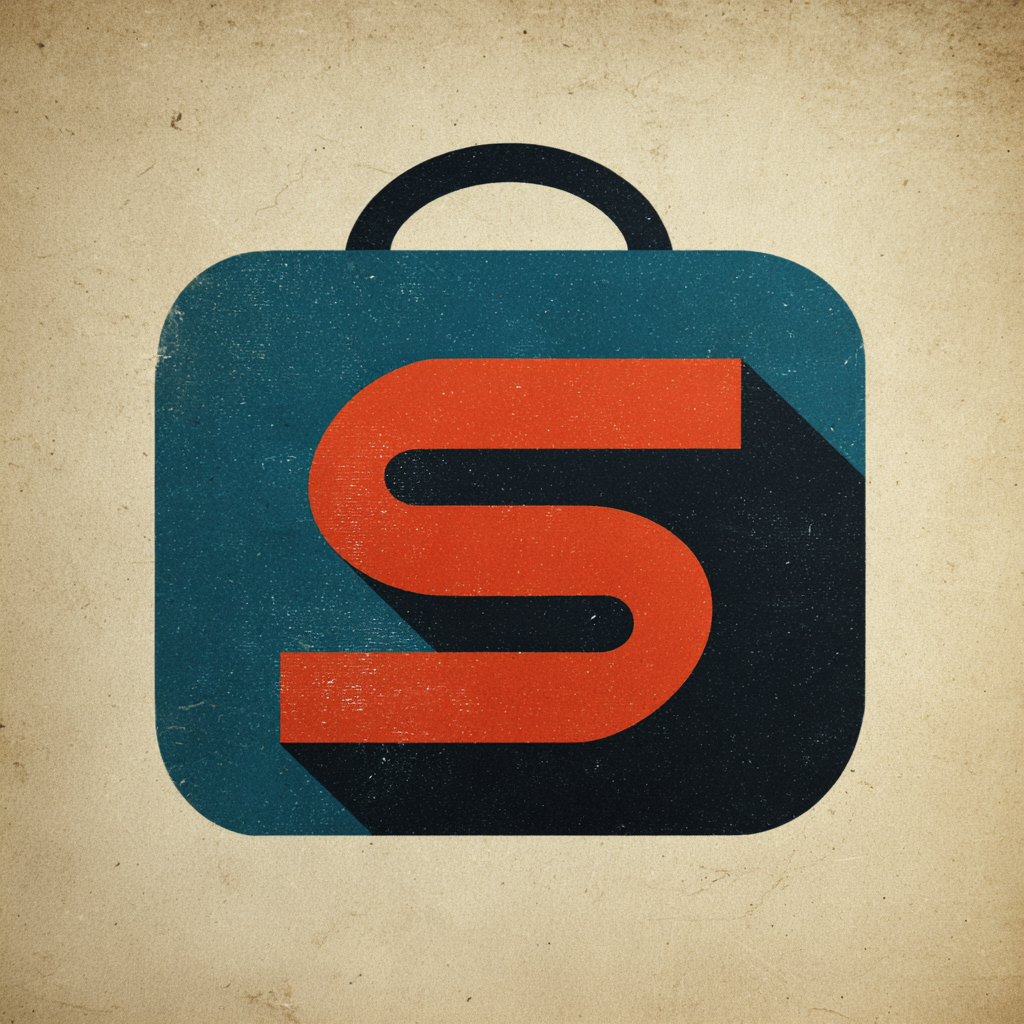
스마트스토어를 처음 시작하거나 리브랜딩을 고민하고 있다면, 가장 먼저 눈에 들어오는 요소 중 하나가 바로 ‘로고’예요. 로고는 브랜드의 첫인상이자, 소비자가 기억하는 가장 강력한 시각적 아이덴티티랍니다. 🛍
특히 요즘처럼 온라인 경쟁이 치열한 시대에는, 스마트스토어의 신뢰감과 차별성을 로고 하나로 보여줘야 할 때가 많아요. 그래서 오늘은 전문가들이 추천하는 스마트스토어 로고 스타일과 디자인 팁을 본격적으로 소개할게요!
🎨 로고 디자인의 중요성과 기원
로고는 단순한 그림이 아니에요. 브랜드의 얼굴이자, 고객과의 첫 만남에서 인상을 좌우하는 핵심 요소예요. 상호명보다도 먼저 시선을 끄는 게 바로 이 ‘로고’인 만큼, 제대로 만들어야 해요.
로고의 역사는 고대 이집트의 상형문자에서 시작됐다고 해요. 상인들이 자신들의 물건에 새긴 상징적인 기호가 현대 로고의 시작이었죠. 이후 중세 유럽에서는 상인의 가문이나 길드를 상징하는 문장(紋章)으로 발전했고, 산업화 시기엔 기업의 공식 마크로 자리 잡았답니다.
스마트스토어처럼 디지털 기반의 비즈니스에서는 로고가 더 중요한 이유가 있어요. 오프라인 매장과 달리 손님이 직접 만지는 물건이나 분위기를 느낄 수 없기 때문에, 화면에서 보여지는 로고와 썸네일이 곧 매장의 '느낌'이 되기 때문이에요.
그만큼 전문성과 신뢰감을 주는 디자인, 그리고 브랜드 정체성이 잘 녹아든 로고는 고객의 기억 속에 깊게 남게 되죠. 스마트스토어 운영자라면 반드시 로고에 신경 써야 해요.
📌 로고 유형별 특성 비교표
로고 유형 특징 예시 브랜드 활용성 텍스트 로고 상호나 브랜드명을 글자 형태로 표현 Google, Samsung 높음 심벌 로고 기호나 그림으로 브랜드 상징화 Apple, Nike 중간 조합형 로고 텍스트 + 아이콘 병행 스타벅스, 배달의민족 매우 높음 앰블럼 로고 문장 형태로 구성된 로고 하버드 대학교, 포르쉐 낮음 내가 생각했을 때 스마트스토어 로고는 '조합형'이 가장 무난하면서도 브랜드성을 잘 살릴 수 있는 스타일 같아요. 단순히 글자만 있는 로고보다, 아이콘이나 이미지가 같이 들어가면 훨씬 기억에 남거든요!
다음은 2025년에 가장 인기 있을 것으로 예상되는 스마트스토어 로고 스타일 트렌드를 살펴볼게요! ✨
🌟 2025년 스마트스토어 로고 트렌드
2025년의 스마트스토어 로고 트렌드는 ‘간결함’과 ‘브랜드 스토리 전달력’이 핵심이에요. 복잡하고 화려한 로고보다는, 직관적이고 명확한 메시지를 주는 디자인이 인기를 끌고 있죠.
요즘 소비자들은 브랜드와의 감성적 연결을 중요하게 생각해요. 그래서 로고 하나에도 감성, 브랜드 철학, 정체성이 담겨 있어야 해요. 한눈에 브랜드 분위기를 알 수 있어야 한다는 뜻이죠.
특히 모바일 환경이 지배적인 지금, 작은 스마트폰 화면에서도 선명하게 보이고 기억에 남을 수 있는 디자인이 필요해요. 아이콘과 텍스트가 조화롭게 구성되어야 하며, ‘응답형 로고(Responsive Logo)’ 형태도 각광받고 있어요.
응답형 로고는 PC, 태블릿, 모바일 등 다양한 환경에 따라 형태나 배치가 달라지는 유연한 디자인을 말해요. 이 방식을 적용하면 어떤 기기에서도 브랜드 일관성을 유지할 수 있답니다.
📊 2025 로고 트렌드 핵심요소
트렌드 요소 설명 추천 적용 대상 미니멀리즘 불필요한 장식 없이 핵심만 표현 생활용품, 의류 플랫 디자인 입체감 없이 깔끔한 2D 형태 디지털 제품, IT 컬러 포인트 한두 가지 색으로 강한 인상 화장품, 식품 모노라인 균일한 두께의 선으로 구성 핸드메이드, 감성몰 응답형 로고 기기별로 최적화되는 변형 로고 모든 스마트스토어 이런 트렌드를 참고해서, 나의 스마트스토어 로고에도 트렌디한 감성을 더해보는 건 어떨까요? 너무 유행만 좇기보다는 브랜드의 개성을 반영하는 게 더 중요하다는 것도 잊지 마세요! 🧠
다음 섹션에서는 실제 전문가들이 추천하는 7가지 스타일을 소개할게요. 스마트스토어 콘셉트에 맞는 로고 스타일을 찾는 데 도움이 될 거예요! 💡
💡 전문가 추천 스타일 7가지
전문 디자이너들이 스마트스토어 로고를 만들 때 자주 추천하는 스타일은 다양하지만, 이 중 7가지가 특히 많이 쓰이고 있어요. 각각의 스타일은 브랜드의 성격, 타깃 고객, 판매 제품과도 연결되기 때문에, 자신의 스토어와 어울리는 스타일을 고르는 게 중요해요.
첫 번째로는 '핸드레터링 스타일'이에요. 이 스타일은 마치 직접 쓴 듯한 감성을 전할 수 있어서 수제 제품, 소규모 공방 브랜드에 잘 어울려요. 개성과 따뜻한 분위기를 동시에 줄 수 있죠.
두 번째는 '미니멀 라인 스타일'인데요, 단순한 선과 형상으로 구성된 이 스타일은 시선을 집중시키고 고급스러운 느낌을 주는 데 탁월해요. IT 제품이나 라이프스타일 브랜드에 적합하죠.
세 번째는 '빈티지 뱃지 스타일'이에요. 예전 마크나 스탬프처럼 디자인된 이 스타일은 클래식하면서도 신뢰감을 주기 때문에 커피, 가구, 캠핑용품 같은 분야에 잘 어울려요.
📋 추천 스타일 7종 비교표
스타일명 주요 특징 추천 업종 핸드레터링 직접 쓴 듯한 감성 공방, 수공예, 디저트 미니멀 라인 단순함, 고급스러움 라이프스타일, 테크 빈티지 뱃지 고전적인 느낌, 신뢰감 커피, 캠핑, 남성브랜드 일러스트형 캐릭터나 도형 중심 아동, 반려동물 심볼 중심 기억에 남는 상징 사용 모든 분야 워드마크형 글자 중심, 이름 강조 브랜드 인지도 필요 분야 모노그램 이니셜 활용 패션, 전문성 강조 브랜드 각 스타일마다 매력이 다르기 때문에, 단순히 유행만 따르기보다는 브랜드 성격과 고객층을 고려해서 선택하는 게 좋아요. 예를 들어, 아동용 제품을 판매하는 스토어라면 일러스트 스타일이 어울리고, 클래식한 맛집이라면 빈티지 뱃지가 딱이에요.
이제 스타일을 골랐다면, 어떤 색과 글자체를 조합해야 더 돋보일까요? 다음 섹션에서 컬러와 타이포그래피에 대해 알려드릴게요! 🎯
🎨 컬러와 타이포그래피의 조화
로고에서 색상과 글꼴은 단순한 시각 요소가 아니라, 브랜드의 분위기와 정체성을 전달하는 언어예요. 어떤 색을 쓰느냐, 어떤 폰트를 고르느냐에 따라 고객이 느끼는 브랜드 이미지는 전혀 달라진답니다.
예를 들어, 파란색은 신뢰감과 안정감을 주고, 빨간색은 열정과 에너지를 상징해요. 녹색은 친환경과 건강을, 검정은 고급스러움과 세련됨을 표현하죠. 스마트스토어가 어떤 제품을 파느냐에 따라 전략적으로 색상을 선택해야 해요.
또한 폰트는 브랜드의 성격을 정하는 핵심 요소 중 하나예요. 굵고 둥근 폰트는 친근하고 캐주얼한 느낌을 주고, 세리프(Serif) 폰트는 클래식하고 고급스러운 분위기를 자아내요. 반면 산세리프(Sans-serif)는 현대적이고 깔끔한 인상을 주죠.
특히 모바일에서 로고가 작게 표시되는 스마트스토어 환경에선 ‘가독성’이 중요해요. 너무 복잡하거나 장식이 많은 폰트는 피하고, 간결하면서도 개성 있는 폰트를 고르는 게 좋아요.
🎯 색상 & 타이포 조합 예시
컬러 느낌 추천 업종 어울리는 폰트 🔵 파랑 신뢰, 안정감 전자제품, 교육 Noto Sans, Pretendard 🔴 빨강 활력, 자극 패션, 뷰티, 식품 BM Jua, Gmarket Sans 🟢 초록 자연, 건강 헬스, 친환경 Cafe24 Ssurround, Nanum Gothic ⚫ 검정 세련됨, 고급 럭셔리, 서비스 Roboto, Spoqa Han Sans 🟡 노랑 유쾌함, 창의 문구, 키즈, 팬시 UhBee Seulvely, Tmon몬소리 컬러를 정할 때는 브랜드의 톤앤매너(Tone & Manner)를 고려해야 해요. 명확한 브랜딩 컬러가 있어야 일관된 인상을 줄 수 있고, 패키지나 배너 디자인에도 연계할 수 있어요.
그리고 너무 많은 색을 쓰는 것보다 1~2가지 포인트 컬러를 정해서 강조하는 방식이 훨씬 깔끔하고 기억에 잘 남아요. 색은 감정을 자극하는 도구이자 기억의 단서이기 때문이에요.
이제 로고 제작을 본격적으로 시작하려고 한다면, 어떤 실수를 조심해야 할까요? 다음 섹션에서는 자주 저지르는 디자인 실수들을 짚어볼게요! 🚫
🚫 로고 디자인 시 피해야 할 실수들
스마트스토어 로고를 만들 때 자주 발생하는 실수들이 있어요. 단순한 실수처럼 보여도 이 때문에 고객이 브랜드를 혼동하거나 아예 관심을 끊을 수 있으니, 꼭 체크해야 해요!
첫 번째 실수는 ‘너무 복잡한 디자인’이에요. 디테일이 많으면 인쇄나 모바일에서 제대로 보이지 않고, 로고가 작게 나올 경우 인식이 어렵죠. 로고는 작게 줄여도 형태가 유지돼야 해요.
두 번째는 ‘유행에만 치우친 디자인’이에요. 일시적으로 인기 있는 스타일을 따르다가 시간이 지나면 구식으로 보일 수 있어요. 트렌드를 참고하되, 브랜드의 고유한 개성을 살리는 게 중요해요.
세 번째는 ‘글꼴 선택 실패’예요. 너무 튀거나 장식적인 폰트를 사용하면 읽기 어렵고, 신뢰감도 떨어져요. 특히 스마트스토어는 모바일로 보는 경우가 많기 때문에 가독성 높은 폰트가 우선이에요.
🧯 피해야 할 디자인 실수 정리표
실수 항목 설명 해결 방법 복잡한 디자인 세부 요소가 많아 시인성 낮음 단순화 & 정리된 구성 유행 따라가기 브랜드 정체성 없이 디자인됨 지속 가능한 스타일 채택 가독성 낮은 글꼴 읽기 어렵고 신뢰감 저하 간결하고 읽기 쉬운 서체 선택 색상 과다 사용 시각적 혼란 유발 1~2가지 컬러로 제한 무료 아이콘 남용 브랜드 고유성 부족 직접 제작 또는 커스터마이징 이 외에도 해상도가 낮은 이미지를 그대로 사용하는 것도 흔한 실수예요. 픽셀이 깨진 로고는 비전문적으로 보이기 때문에, 반드시 벡터 기반(AI, SVG 등) 파일로 만들어야 해요.
또한, 너무 많은 요소를 담으려는 욕심도 피해야 해요. "이것도 넣고 저것도 보여주자!"는 마음은 이해되지만, 결과적으로는 메시지가 흐려지고 인식이 어려워져요. 핵심 하나만 담는 것이 오히려 강력한 메시지가 될 수 있어요.
로고 디자인은 브랜드의 얼굴을 만드는 작업이기 때문에, 이 실수들만 피하더라도 훨씬 완성도 높은 결과물을 만들 수 있어요. 💪
Q4. 로고 색상은 몇 가지가 적당한가요?
A4. 기본적으로는 메인 컬러 1개와 보조 컬러 1개를 조합하는 방식이 좋아요. 너무 많은 색을 쓰면 혼란을 줄 수 있어요.
Q5. 스마트스토어 썸네일에 로고를 꼭 넣어야 하나요?
A5. 썸네일에 로고가 들어가면 브랜드 통일성을 높일 수 있어요. 특히 반복 노출 시 고객이 더 빨리 인식하게 되죠.
Q6. 스마트폰 환경에서도 잘 보이는 로고는 어떻게 만드나요?
A6. 단순하고 선명한 형태로, 복잡한 그림 없이 간결한 텍스트 또는 아이콘을 사용하는 게 좋아요. 너무 얇거나 복잡한 요소는 축소 시 흐려질 수 있어요.
Q8. 로고는 언제 바꾸는 게 좋을까요?
A8. 브랜드 콘셉트 변경, 타겟층 변화, 리브랜딩이 필요한 시점에 변경을 고려할 수 있어요. 단, 기존 고객과의 인식 단절을 줄이기 위해 점진적인 변화가 중요해요.